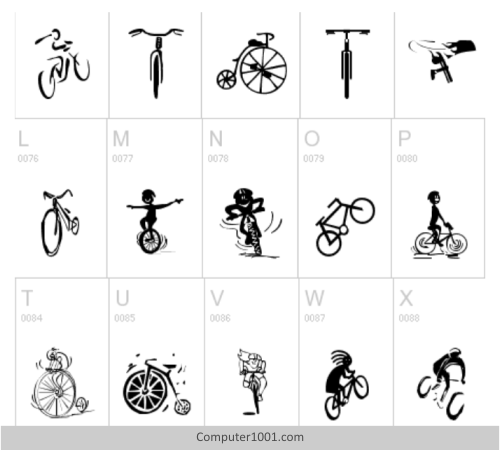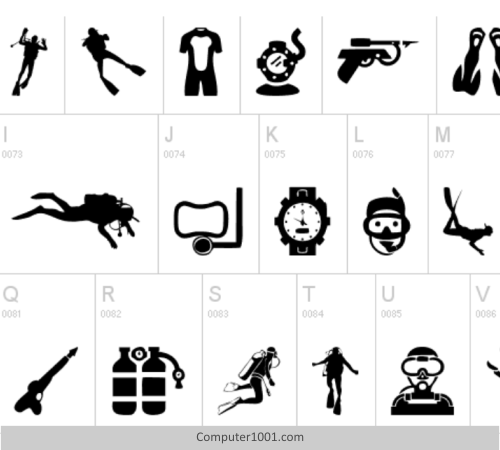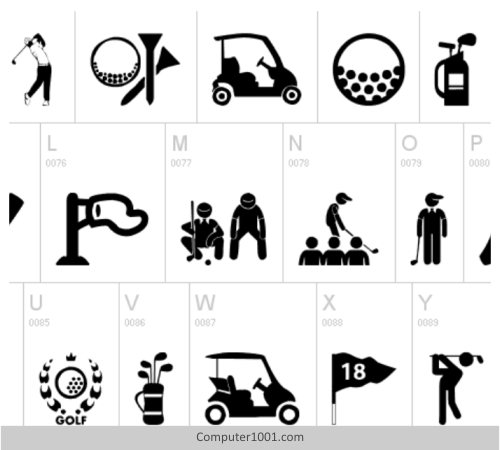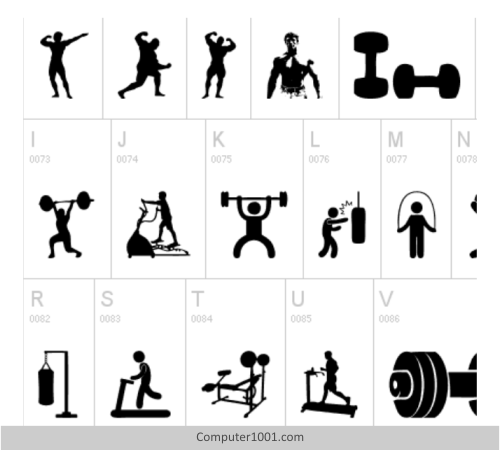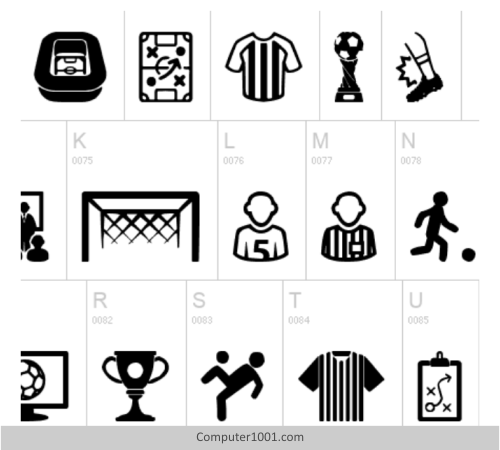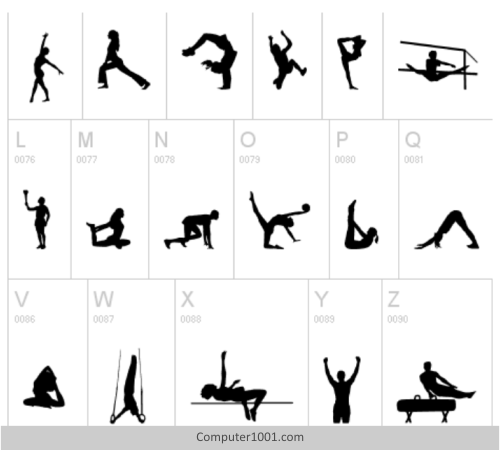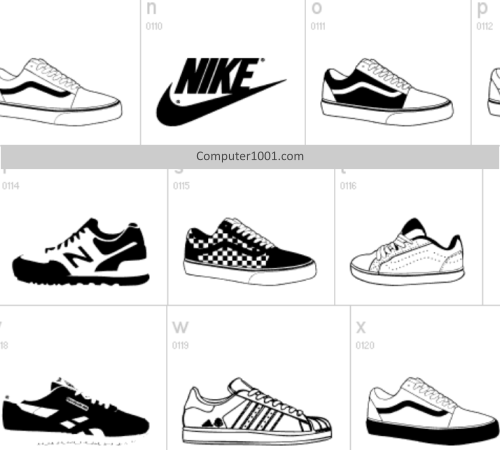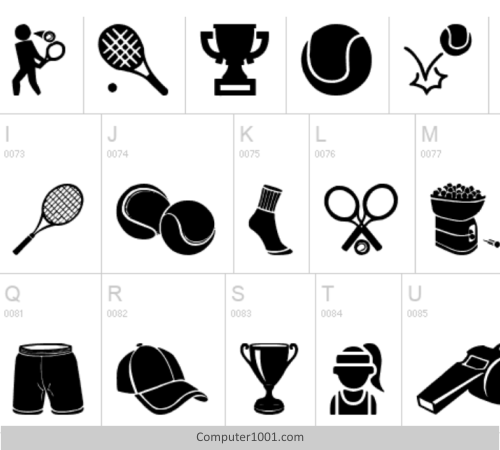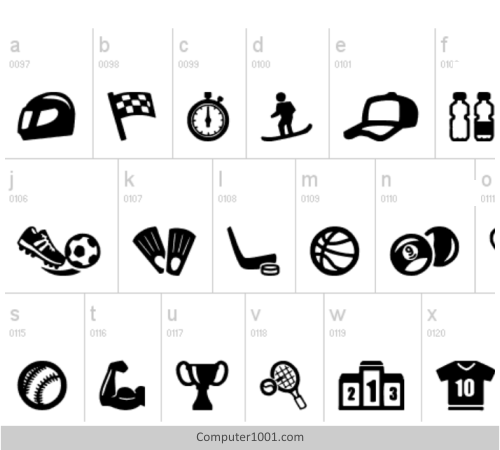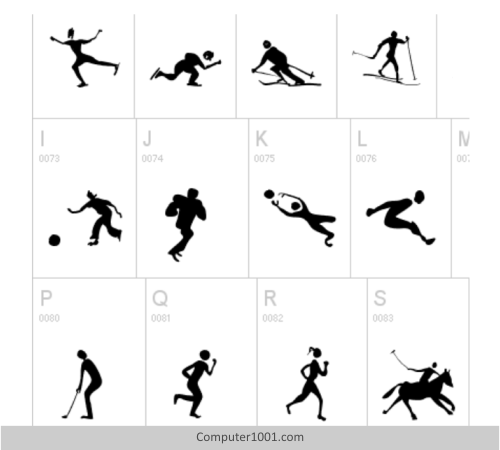
16 Font Olahraga Gratis
Di artikel ini, Computer 1001 menyajikan 16 font gambar tema olahraga yang dapat diunduh gratis di Dafont dan Fontspace.
Font Sports 1
Font ini memiliki 53 gambar untuk berbagai cabang olahraga. Antara lain: bisbol, atletik, berkuda, tinju, anggar, hoki, binaraga. Juga ada gambar kegiatan memancing dan berkemah.
Font Sports 1
Sports 1 Font
Font ini serupa dengan font di atas dan hanya ada 16 karakter. Namun, gambar pada font ini memiliki warna yang lebih terang dan ada gambar start renang yang indah.
Font Olahraga Sports 1
Font Sports and Hobbies
Font ini memiliki 89 gambar peralatan olahraga, seperti raket, bola, sarung tangan, sepatu, baju, dan topi olahraga; ring basket, piala, serta mata kail pancing, tenda, ransel, dan lain-lain.
Font Sports and Hobbies
Font Olahraga Sportive
Font ini memiliki gambar untuk olahraga angkat besi, golf, polo, atletik, lari, renang, ski air, dan lain-lain.
Font Olahraga Sportive
Font Go Go Sports
Font ini memiliki gambar bola dan peralatan untuk berbagai cabang olahraga. Juga ada gambar peluit, sport jersey, podium, dan piala.
Font Go Go Sports
Font Gambar Olahraga Sports TFB
Font ini memiliki banyak gambar siluet gerakan senam artistik dan atletik (lari estafek, lompat galah, lompat jauh). Juga ada siluet dayung, basket, badminton, renang, angkat berat atau angkat besi.
Font Gambar Olahraga Sports TFB
Font Gambar Sepatu Olahraga Sneakers
Font gambar berbagai model sepatu kets.
Font Gambar Sepatu Olahraga Sneakers
Font Sepak Bola Soccer Icons
Font gambar icon tema sepak bola. Antara lain: pemain bola, wasit, komentator, serta berbagai model peluit, stadium, gawang, kartu merah/kuning, medali, dan piala.
Font Sepak Bola Soccer Icons
Font Gambar Gym
Font gambar orang yang sedang berolahraga di gym dan berbagai peralatan, seperti barbell, dumbbell, treadmill, sepeda statis, dan berbagai pose binaragawan.
Font Gambar Gym
Font Gambar Tennis
Font gambar untuk olahraga tenis. Antara lain: gambar raket dan bola tenis, piala, sepatu, kaos kaki, kostum tenis untuk pria dan wanita, serta lapangan dan kursi wasit tenis.
Font Gambar Tennis
Font Gambar Cycling
Font gambar untuk olahraga bersepeda. Ada berbagai model sepeda, termasuk sepeda antik dengan roda depan yang lebih besar.
Font Gambar Cycling
Font Gambar Golf Icons
Font gambar untuk olahraga golf.
Font Gambar Golf Icons
Font Olahraga Surf
Font gambar peralatan dan pose orang yang sedang berselancar.
Font Olahraga Surf
Font Gambar Diving
Font gambar tema menyelam. Selain gambar orang-orang yang sedang diving; juga ada gambar masker dan snorkel, fins, pakaian menyelam, tangki selam, serta gambar ikan dan hewan laut.
Font Gambar Diving
Font Gambar Yogafont
Font gambar siluet orang-orang yang sedang melakukan gerakan yoga.
Font Gambar Yoga
Font Gambar Tai-Chi Silhouette
Font gambar siluet orang yang sedang melakukan berbagai gerakan tai chi.
Font Gambar Tai-Chi Silhouette